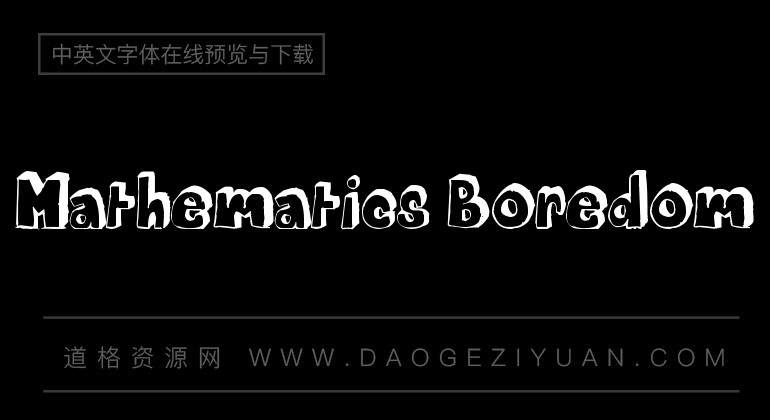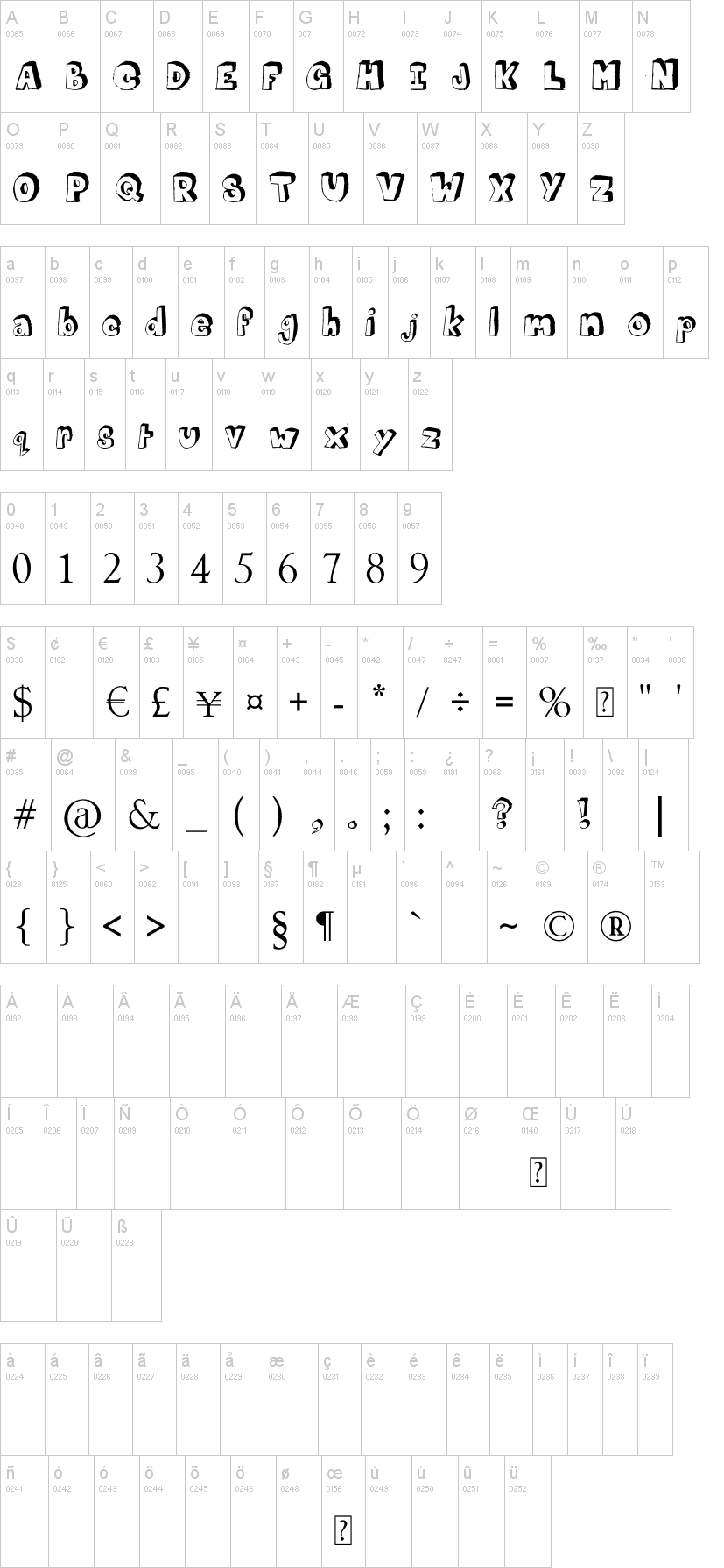
Mathematics Boredom
Mathematics Boredom是一款由FontMesa创作的字体,它拥有一种独特的外观,具有抽象的几何形状,可以帮助您在任何场合创建精美的设计。它具有细节丰富的曲线,可以帮助您创建出视觉上令人惊叹的设计。它也具有极高的可读性,可以清楚地传达您的想法。它可以用于创建海报,标志,标签,品牌标识,网页,平面设计,印刷品,展览等。
Mathematics Boredom是一款非常不错的手写艺术字体,具有很好的视觉感,适合于文化类的宣传设计、商业类品牌的广告和产品包装设计以及个性化文字排版等较多场景。
Mathematics Boredom字符映射图